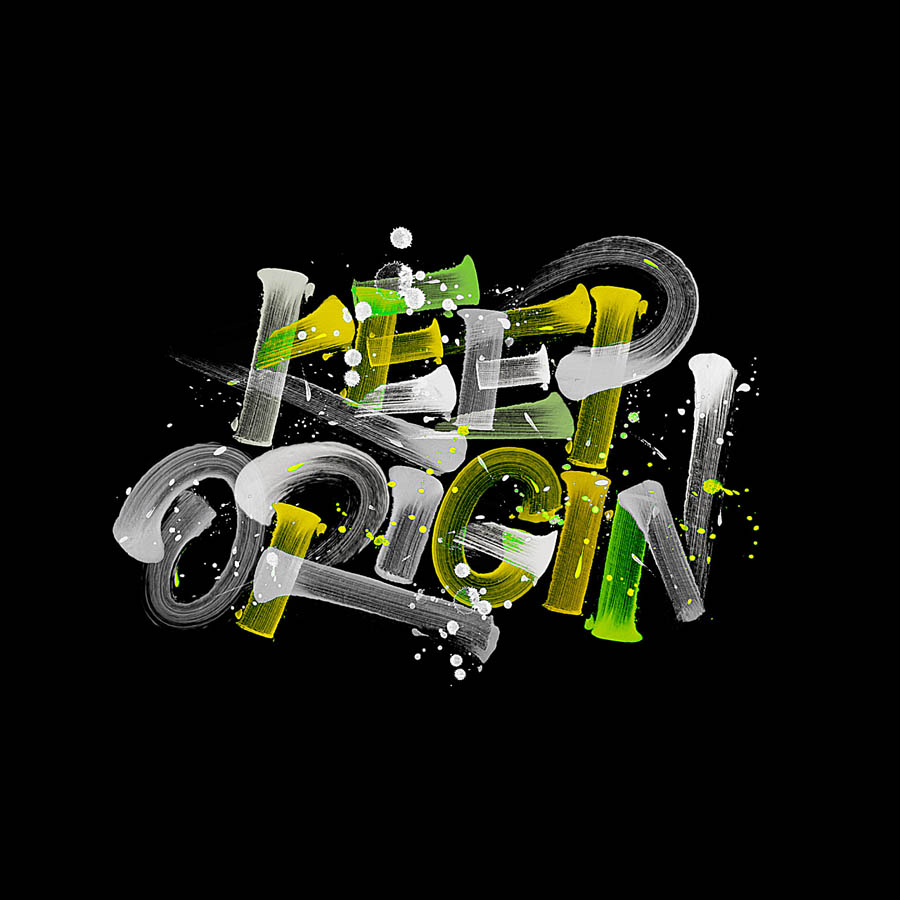
文字设计的科学:使用字体、大小和间距优化沟通 (文字设计的科学性原理)
大小和间距优化沟通
文字设计是一门科学,通过使用不同的字体、大小和间距来优化沟通的有效性。熟练掌握这些原则可以帮助你创建易于阅读、理解和吸引受众的文本。
字体
字体是最重要的设计元素之一。它可以设置文本的基调并影响其可读性。选择字体时,请考虑以下因素:
• 可读性:选择易于在各种设备和屏幕尺寸上阅读的字体。
• 可辨识度:避免使用不熟悉的或难以辨认的字体。
• 品牌一致性:如果你的品牌有特定的字体,请在所有沟通中使用它以保持一致性。
大小
字体大小对于确保文本的可读性至关重要。文本太小会难以阅读,而文本太大